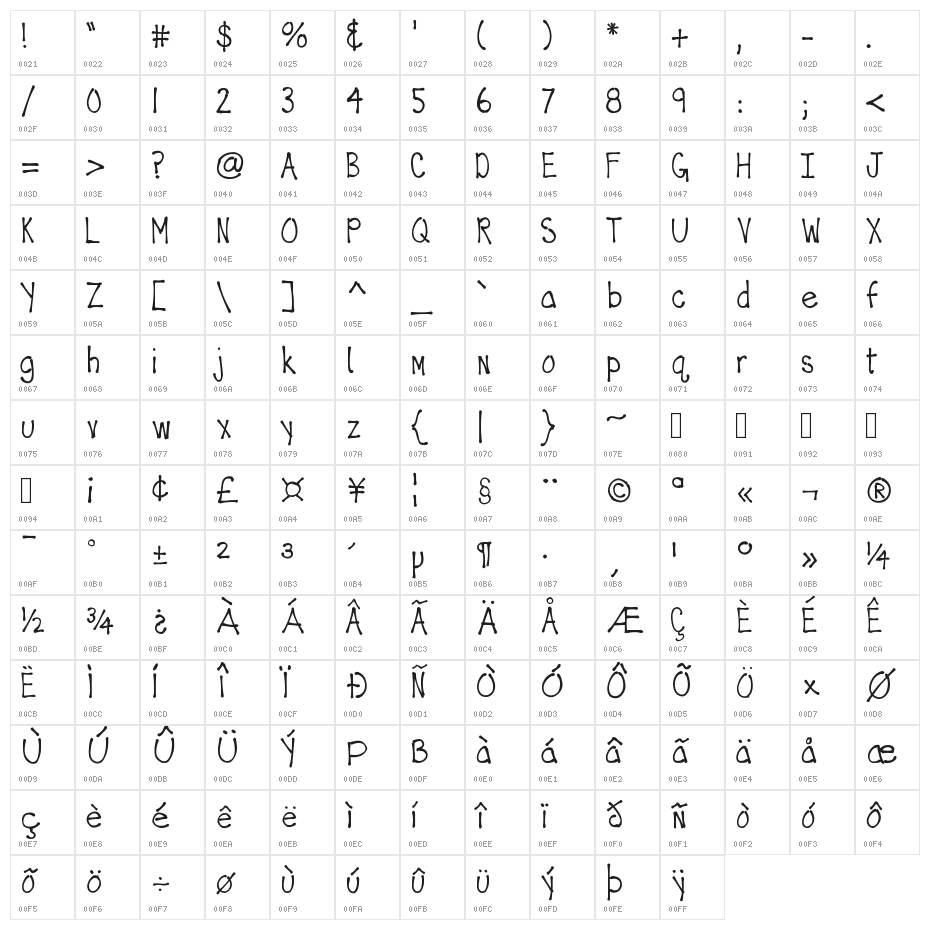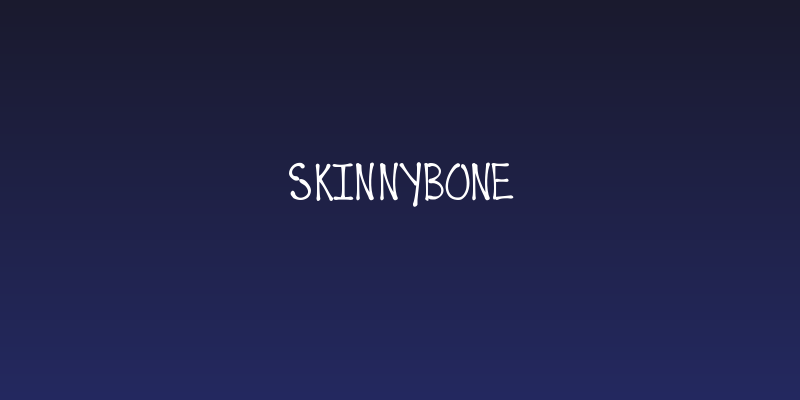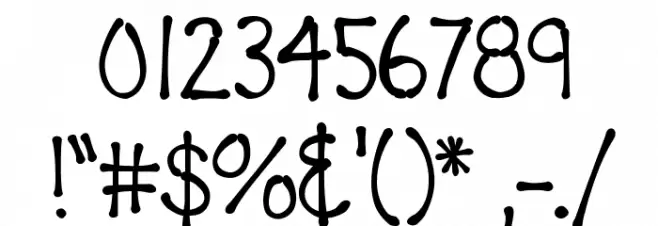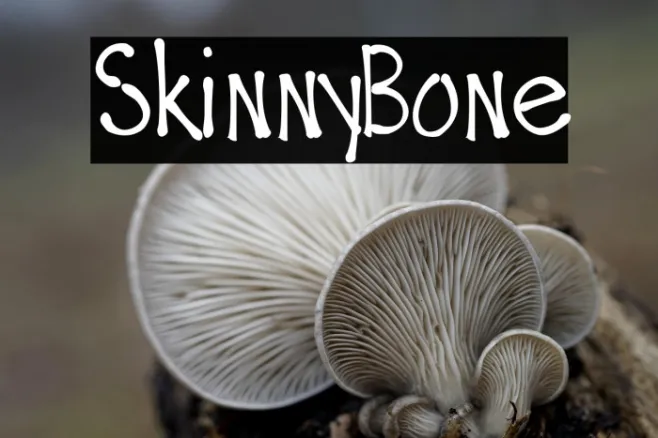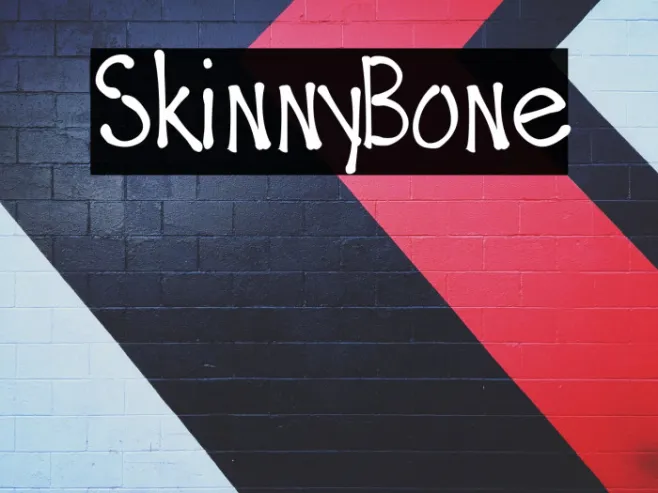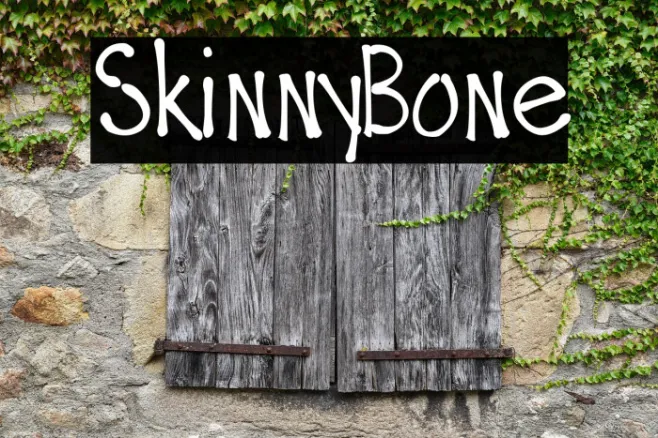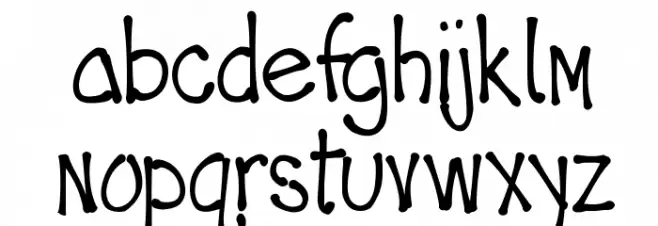
SkinnyBone Font
| Gesamtstil | Whimsical |
| Anwendungsfall | Headlines, Logos, Casual Text |
| Vorgeschlagene Projekte | Ideal for children's books, greeting cards, playful branding, and casual invitations. |